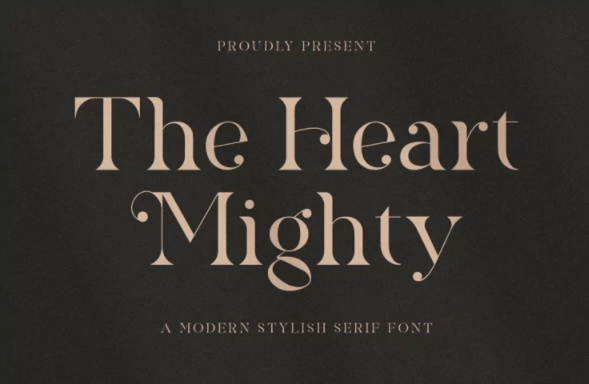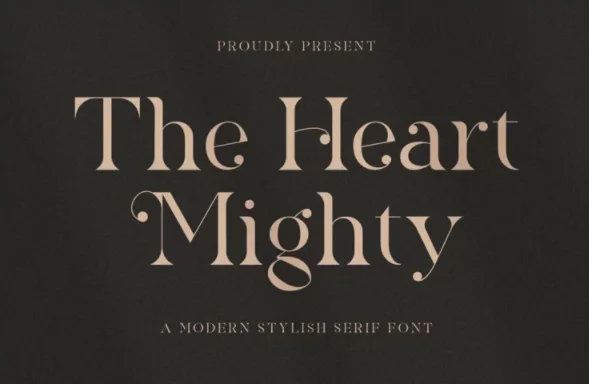
[Fontbundles] The Heart Mighty Font (2021)
Название: The Heart Mighty Font (2021)
The Heart Mighty - нежный и элегантный шрифт с засечками. Вы можете использовать этот современный шрифт с засечками, лигатурами и стилистическим набором для оформления моды, журналов, кулинарных сайтов, цитат, постов в социальных сетях, этикеток и многого другого! Смело добавляйте его в свои любимые творения и позвольте себе поразиться полученному результату.